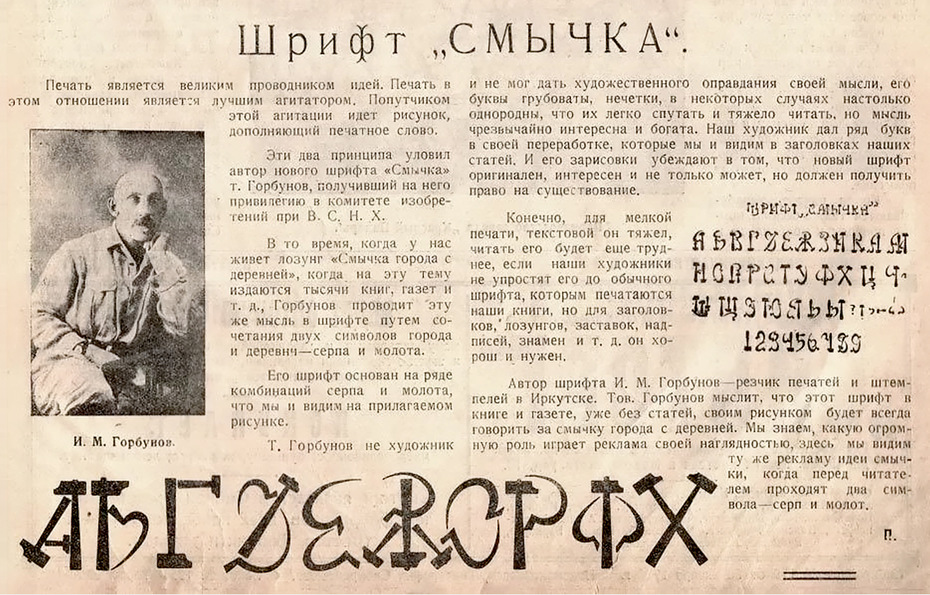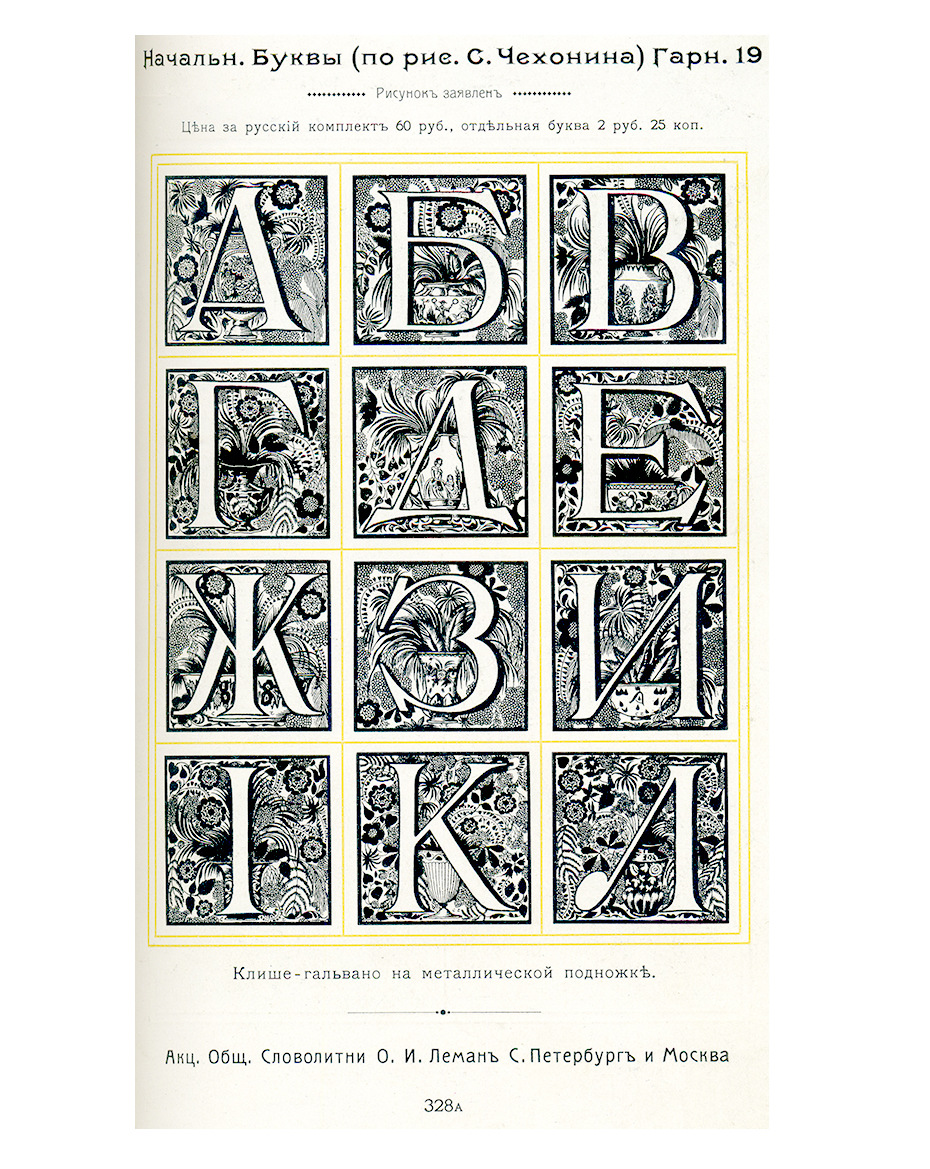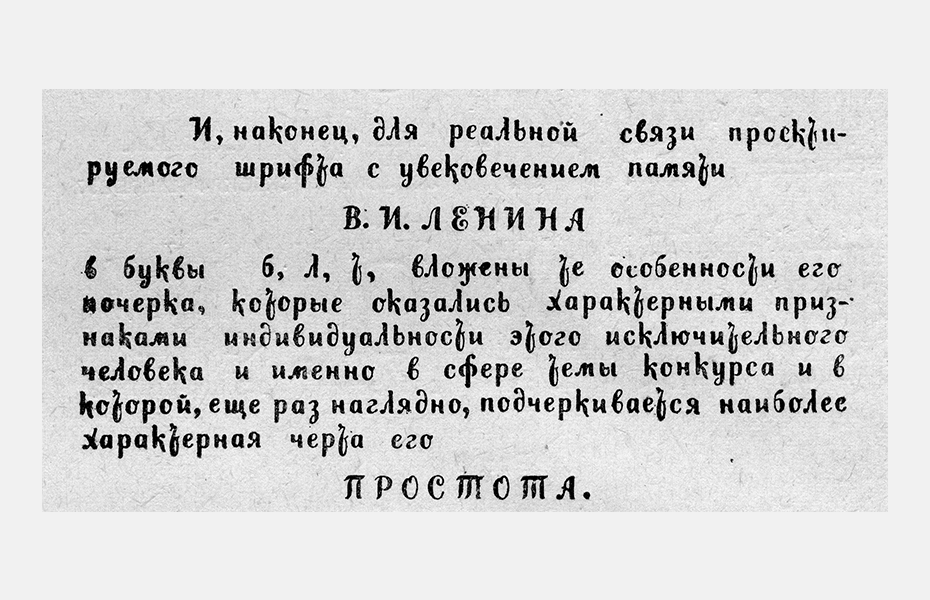
Из истории конкурсов шрифтового дизайна
Константин Головченко
еж­ду­на­род­ные кон­кур­сы шриф­то­во­го ди­зай­на се­го­дня — не­пло­хой мар­кер со­сто­я­ния ин­ду­стрии, при­чём не толь­ко про­фес­си­о­наль­ной, но и сту­ден­че­ской. Type design competition — ма­ши­на с от­ла­жен­ным за мно­го лет ме­ха­низ­мом и ин­ди­ви­ду­аль­ны­ми осо­бен­но­стя­ми в за­ви­си­мо­сти от ре­гла­мен­та, со­ста­ва жю­ри и ме­то­дов оцен­ки ра­бот. Всё ча­ще в кон­кур­сах по­яв­ля­ет­ся от­дель­ная ка­те­го­рия для не­ла­тин­ских шриф­тов, в том чис­ле и на осно­ве ки­рил­ли­цы. Ди­зай­нер, ис­то­рик шриф­та Кон­стан­тин Го­лов­чен­ко дол­гое вре­мя изу­чал ис­то­рию кон­кур­сов ки­рил­ли­че­ских шриф­тов и со­брал уни­каль­ные ар­хив­ные ма­те­ри­а­лы о шриф­тах-участ­ни­ках и ху­дож­ни­ках. Мы пуб­ли­ку­ем пер­вую часть его ис­сле­до­ва­ния — о том, ка­кие бы­ли кон­кур­сы в до­ре­во­лю­ци­он­ной Рос­сии и в пер­вые го­ды со­вет­ской вла­сти. Ре­дак­ция
Часть I. «Ка­кая ску­ка ри­со­вать шриф­ты».
Пер­вые кон­кур­сы шриф­то­во­го ди­зай­на
Са­мый дав­ний из из­вест­ных мне кон­кур­сов был ор­га­ни­зо­ван сло­во­лит­ней Ле­ма­на в 1912 го­ду. Пред­се­да­те­лем её прав­ле­ния на то вре­мя был Иосиф Иоси­фо­вич Ле­ман, один из сы­но­вей осно­ва­те­ля — Оси­па Ива­но­ви­ча Ле­ма­на. Иосиф Иоси­фо­вич уна­сле­до­вал не толь­ко свою до­лю в пред­при­я­тии от­ца, но и ис­крен­ний ин­те­рес к ти­по­гра­фи­ке, шриф­там и из­да­тель­ско­му де­лу. Кро­ме то­го, он был из­вест­ным биб­лио­фи­лом, кол­лек­ци­о­не­ром и ме­це­на­том, ав­то­ром двух книг — «Очерк раз­ви­тия и опи­са­ние ма­стер­ских Сло­во­лит­ни О. И. Ле­ман в Санкт-Пе­тер­бур­ге» и «Гра­вю­ра и ли­то­гра­фия».
Иосиф Ле­ман по­сто­ян­но ис­кал воз­мож­но­сти и по­ощрял лю­бые по­пыт­ки со­зда­ния но­вых ка­че­ствен­ных ри­сун­ков шриф­тов. На­при­мер, ко­гда в 1905 го­ду Игорь Эм­ма­ну­и­ло­вич Гра­барь со­би­рал­ся вы­пус­кать свой жур­нал «Вест­ник ис­кусств» (этот про­ект не уда­лось ре­а­ли­зо­вать), пред­по­ла­га­лось на­би­рать его но­вым шриф­том, ри­су­нок ко­то­ро­го дол­жен был ис­пол­нить М. В. До­бу­жин­ский. В пе­ре­пис­ке с ним Гра­барь со­об­щал:
«Се­го­дня же по­лу­чил и све­де­ния от­но­си­тель­но пер­спек­ти­вы иметь свой соб­ствен­ный шрифт. Если ри­су­нок Ле­ма­ну по­нра­вит­ся, то он ни­че­го не возь­мёт за от­лив­ку. <…> Ей-бо­гу, сто­ит ов­чин­ка вы­дел­ки. Шут­ка ли ска­зать: со­здать на­ко­нец-то ху­до­же­ствен­ный шрифт в Рос­сии. <…> Но на­до ид­ти на риск; если Ле­ма­ну, под­ле­цу, не по­нра­вит­ся, то Ва­ших 15 букв про­па­дут да­ром (проб­ных)».
Та­ким об­ра­зом, ор­га­ни­зо­ван­ный в 1912 го­ду кон­курс (по­след­ний срок сда­чи ра­бот — 15 ок­тя­бря) был оче­ред­ной по­пыт­кой со­зда­ния но­вых шриф­тов и по­пол­не­ния ас­сор­ти­мен­та сло­во­лит­ни, что да­ло бы ей пре­иму­ще­ство пе­ред до­воль­но силь­ны­ми кон­ку­рен­та­ми — в пер­вую оче­редь, сло­во­лит­ней Берт­голь­да.
Ге­ор­гий (Егор) Ива­но­вич Нар­бут [25 фе­вра­ля (9 мар­та) 1886, Нар­бу­тов­ка, Чер­ни­гов­ская гу­бер­ния — 23 мая 1920, Ки­ев]. Рус­ский и укра­ин­ский ху­дож­ник-гра­фик, ил­лю­стра­тор. Ма­стер ри­со­ван­но­го шриф­та, в пе­тер­бург­ский пе­ри­од жиз­ни Нар­бут офор­мил боль­шое ко­ли­че­ство книг в са­мых раз­ных жан­рах. На об­лож­ках и ти­туль­ных ли­стах он вир­ту­оз­но со­зда­вал об­раз­ные и пла­стич­ные над­пи­си  — от ими­та­ции древ­не­рус­ских по­чер­ков до ам­пир­ных букв. Фо­то не по­зд­нее 1917 го­да.
Ин­те­рес­ные сви­де­тель­ства об этом кон­кур­се мож­но по­черп­нуть из пе­ре­пис­ки од­но­го из участ­ни­ков, Г. И. Нар­бу­та, с же­ной. Ко вре­ме­ни опи­сы­ва­е­мых со­бы­тий Ге­ор­гий Ива­но­вич Нар­бут уже был при­знан­ным ху­дож­ни­ком-гра­фи­ком и со­сто­ял в ху­до­же­ствен­ном объ­еди­не­нии «Мир ис­кус­ства». Ещё в дет­стве шриф­ты вы­зы­ва­ли у не­го жи­вой ин­те­рес, в гим­на­зии он по соб­ствен­ной ини­ци­а­ти­ве пе­ре­ри­со­вы­вал бук­вы из Остро­ми­ро­ва Еван­ге­лия. По­том был пе­ре­езд в Пе­тер­бург, учё­ба у Би­ли­би­на, До­бу­жин­ско­го, Бак­ста, за­тем в Мюн­хе­не у Ш. Хол­ло­ши, мно­же­ство ис­пол­нен­ных для книг и жур­на­лов ил­лю­стра­ций, об­ло­жек, над­пи­сей.
Тем уди­ви­тель­нее в све­те вы­ше­из­ло­жен­но­го мо­гут вы­гля­деть ци­та­ты из не­ко­то­рых его пи­сем:
«Ма­ло я сей­час те­бе пи­шу; ты не оби­жай­ся, моя ра­дость. Ведь я пи­шу толь­ко ве­че­ром и по­чти все­гда уста­лый к это­му вре­ме­ни. Ра­бо­таю сей­час над шриф­том: ад­ская ску­ка… Если бы ты зна­ла, Ве­ру­ся, ка­кая ску­ка ри­со­вать шриф­ты, то есть бук­вы. Но еще при­дет­ся си­деть за этим дня два-три, а я уже по­чти не имею сил… Се­го­дня си­дел один, как перст, це­лый день и со­всем не от­ры­вал­ся от ра­бо­ты. Устал, как ты мо­жешь пред­ста­вить, не­ве­ро­ят­но, очень. Глав­ное, что эта ра­бо­та та­кая не­за­хва­ты­ва­ю­щая, скуч­ная-пре­скуч­ная».
За­кон­чив ра­бо­ту и от­пра­вив к сро­ку об­раз­цы, Нар­бут яв­но ощу­ща­ет об­лег­че­ние: «Сей­час не­мно­го опра­вил­ся по­сле пи­са­ния раз­лич­ных шриф­тов… Я се­бя чув­ствую от­лич­но, бодро и хо­ро­шо, а глав­ное, про­шло то гне­ту­щее на­стро­е­ние и апа­тия, пре­сле­до­вав­шие ме­ня всё вре­мя на про­шлой не­де­ле».
Воз­ни­ка­ет есте­ствен­ный во­прос: как же мог на­пи­сать по­доб­ное этот ма­стер, про­жив­ший до­воль­но ко­рот­кую, но на­сы­щен­ную жизнь и оста­вив­ший це­лый ряд уче­ни­ков и по­сле­до­ва­те­лей, ма­стер, в на­сле­дии ко­то­ро­го — мно­же­ство ра­бот, и се­го­дня слу­жа­щих вдох­но­ве­ни­ем для ди­зай­не­ров шриф­та?
Воз­мож­но, под­сказ­кой для от­ве­та мо­жет слу­жить ра­бо­та, за­няв­шая на этом кон­кур­се пер­вое ме­сто. Она при­над­ле­жит дру­го­му чле­ну «Ми­ра ис­кус­ства», Сер­гею Че­хо­ни­ну. Его про­ект дей­стви­тель­но был ре­а­ли­зо­ван в ме­тал­ле в ка­че­стве на­бор­но­го шриф­та. Од­на­ко шрифт этот до­воль­но спе­ци­фи­че­ский — он был пред­на­зна­чен для бук­виц. От­ли­чие по­доб­ных шриф­тов в том, что бук­вы в них, как пра­ви­ло, не пред­по­ла­га­ют вза­и­мо­дей­ствия друг с дру­гом, яв­ля­ясь по су­ти от­дель­ным эле­мен­том на­бо­ра.
По­бе­да имен­но та­кой ра­бо­ты мо­жет го­во­рить о том, что для Нар­бу­та и осталь­ных ху­дож­ни­ков, при­вык­ших ри­со­вать над­пи­си, за­да­ча по со­зда­нию на­бор­но­го шриф­та ока­за­лась слиш­ком тя­жёлой. Ведь в на­ри­со­ван­ной над­пи­си каж­дая бук­ва вза­и­мо­дей­ству­ет лишь со сво­и­ми со­се­дя­ми по стро­ке, на­бор­ный же шрифт тре­бу­ет мак­си­маль­но гар­мо­нич­но­го со­че­та­ния всех зна­ков в лю­бых ком­би­на­ци­ях. По­хо­жие си­ту­а­ции мож­но до­ста­точ­но ча­сто на­блю­дать и сей­час, ко­гда ди­зай­нер пы­та­ет­ся со­здать шрифт на осно­ве ри­со­ван­ных букв то­го или ино­го ху­дож­ни­ка, но по­сле точ­ной их от­ри­сов­ки в век­тор­ном фор­ма­те осо­зна­ёт, что в та­ком ви­де они го­дят­ся лишь для вос­про­из­ве­де­ния ис­ход­ной над­пи­си. По вос­по­ми­на­ни­ям со­вре­мен­ни­ков, Нар­бут до кон­ца жиз­ни на­де­ял­ся со­здать на­бор­ный шрифт, «но со­зда­вать шрифт — это „боль­шая мо­ро­ка“: нуж­но про­ра­ба­ты­вать каж­дую бук­ву, каж­дую ме­лочь при­ни­мать во вни­ма­ние, вы­ме­рять».
На­бор­ная бук­ви­ца С. Че­хо­ни­на. Жур­нал «Рус­ское ис­кус­ство» №1. 1923.
Тем не ме­нее приём, с по­мо­щью ко­то­ро­го по­бе­дил Че­хо­нин, на мой взгляд, впол­не при­ме­ним и в на­ше вре­мя. И се­го­дня ди­зай­нер, спо­соб­ный со­зда­вать по-на­сто­я­ще­му ин­те­рес­ные шриф­то­вые фор­мы, но не име­ю­щий до­ста­точ­но на­вы­ков, вре­ме­ни, тер­пе­ния или же­ла­ния для то­го, что­бы вы­пол­нять кро­пот­ли­вую ра­бо­ту по со­зда­нию «обыч­но­го» шриф­та, мо­жет по­про­бо­вать се­бя в раз­ра­бот­ке де­ко­ра­тив­ных ини­ци­а­лов — и та­кой про­ект име­ет шанс быть от­ме­чен­ным на кон­кур­се.
За­вер­шая рас­сказ об ор­га­ни­зо­ван­ном сло­во­лит­ней Ле­ма­на кон­кур­се, нуж­но упо­мя­нуть, что он пред­по­ла­гал де­неж­ное воз­на­гра­жде­ние. Точ­ный его раз­мер нам, к со­жа­ле­нию, не­из­ве­стен, но Нар­бут, на­при­мер, в слу­чае по­бе­ды на вы­ру­чен­ные день­ги рас­счи­ты­вал ку­пить ро­яль.
Со­вет­ские кон­кур­сы 1920-х го­дов
Сле­ду­ю­щие кон­кур­сы, ко­то­рые мы рас­смот­рим, от­но­сят­ся к 20-м го­дам про­шло­го ве­ка. В 1927 го­ду бу­ду­щий член-кор­ре­спон­дент Ака­де­мии на­ук, про­фес­сор Алек­сей Алек­се­е­вич Си­до­ров, не­до­уме­вая, пи­сал: «По­пыт­ки ре­фор­мы очер­та­ния шриф­та, со­зда­ния но­во­го не шли даль­ше ор­га­ни­за­ции не­сколь­ких кон­кур­сов, кон­чив­ших­ся бес­плод­но. По­че­му? В ма­сте­рах у нас не­до­стат­ка нет. Нет не­до­стат­ка и в уме­нии клас­си­фи­ци­ро­вать и ра­зо­брать­ся».
Дей­стви­тель­но, в то вре­мя пред­при­ни­мал­ся ряд ини­ци­а­тив по про­ве­де­нию кон­кур­сов, ни один из ко­то­рых, как спра­вед­ли­во от­ме­чал А. А. Си­до­ров, не дал прак­ти­че­ских ре­зуль­та­тов.
Пер­вый со­вет­ский шриф­то­вой кон­курс от­но­сит­ся, ве­ро­ят­но, к 1920 го­ду. Он был ор­га­ни­зо­ван Пет­ро­град­ским от­де­ле­ни­ем Го­су­дар­ствен­но­го кни­го­из­да­тель­ства, рас­про­стра­нив­шим сле­ду­ю­щее объ­яв­ле­ние:
«На­сто­я­щим до­во­дит[ся] до све­де­ния всех ху­дож­ни­ков-гра­вё­ров, гра­вё­ров-пу­ан­со­ни­стов и гра­вё­ров-ли­то­гра­фов, что… ор­га­ни­зо­ван кон­курс по со­зда­нию но­вых рус­ских шриф­тов, а имен­но:
1) шриф­та для учеб­ни­ков и учеб­ных по­со­бий,
2) шриф­та для книг бел­ле­три­сти­че­ско­го со­дер­жа­ния, жур­на­лов и га­зет и
3) шриф­та для книг и жур­на­лов, рос­кош­но из­да­ва­е­мых»
Так­же нуж­но от­ме­тить кон­курс, ор­га­ни­зо­ван­ный в 1923 го­ду. В де­ка­бре 1922 го­да по ини­ци­а­ти­ве К. С. Кузь­мин­ско­го при Го­су­дар­ствен­ном из­да­тель­стве бы­ла со­зда­на «Ко­мис­сия по изу­че­нию рус­ских ил­лю­стри­ро­ван­ных из­да­ний», поз­же пе­ре­име­но­ван­ная в «Ко­мис­сию по изу­че­нию ис­кус­ства кни­ги». Её пред­се­да­те­лем стал сам Кузь­мин­ский, в со­став во­шли В. Я. Ада­рю­ков, К. С. Ва­х­ра­ме­ев, М. А. До­бров, А. Г. Ка­лаш­ни­ков, Н. П. Ки­се­лёв, И. И. Ла­за­рев­ский, В. П. По­лон­ский, А. А. Си­до­ров, В. А. Фа­вор­ский, В. Д. Фа­ли­ле­ев, П. П. Ши­ба­нов, М. И. Щел­ку­нов, П. Д. Эт­тин­гер и се­кре­тарь — В. В. Голь­цев.
В са­мом на­ча­ле её ра­бо­ты был под­нят во­прос о со­зда­нии но­во­го ти­по­граф­ско­го шриф­та, так как су­ще­ству­ю­щие при­зна­ва­лись уста­рев­ши­ми и не от­ве­ча­ю­щи­ми тре­бо­ва­ни­ям со­вре­мен­но­сти. На за­се­да­ни­ях этой ко­мис­сии бы­ло за­слу­ша­но мно­же­ство до­кла­дов о шриф­те: «Вве­де­ние в те­о­рию шриф­тов» А. А. Си­до­ро­ва, «Прин­ци­пы кра­со­ты шриф­та» М. И. Щел­ку­но­ва, «Биб­лио­гра­фи­че­ский ука­за­тель „Рус­ские ти­по­граф­ские шриф­ты“» В. Я. Ада­рю­ко­ва, «Что тре­бу­ет от шриф­тов про­цесс чте­ния» В. И. Яз­виц­ко­го, «Ком­по­зи­ци­он­ные осно­вы шриф­та» В. Д. Фа­ли­ле­е­ва, «Шрифт для дет­ской и на­род­ной ли­те­ра­ту­ры» К. С. Ва­х­ра­ме­е­ва, «Ме­то­ди­ка ис­сле­до­ва­ния фи­зио­ло­ги­че­ско­го дей­ствия книж­но­го шриф­та» А. Г. Ка­лаш­ни­ко­ва, «Шриф­ты для ти­туль­ных ли­стов» Н. В. Маш­ков­це­ва, «О книж­ных укра­ше­ни­ях» М. А. До­бро­ва и др.
За­тем был ор­га­ни­зо­ван за­кры­тый кон­курс на со­зда­ние экс­либ­ри­сов для Биб­лио­те­ки Го­сиз­да­та и Ар­хи­ва Рос­сий­ской Цент­раль­ной книж­ной па­ла­ты, по­сле успеш­но­го за­вер­ше­ния ко­то­ро­го на за­се­да­нии 3 ок­тя­бря 1923 го­да бы­ло при­ня­то ре­ше­ние о про­ве­де­нии за­кры­то­го кон­кур­са на со­зда­ние книж­но­го шриф­та для на­бо­ра дет­ской ли­те­ра­ту­ры. К уча­стию в нём при­вле­ка­лись В. А. Фа­вор­ский, Н. И. Пис­ка­рёв, Н Н. Ку­пре­я­нов, В. Д. Фа­ли­ле­ев, А. Н. Лео и дру­гие ху­дож­ни­ки Моск­вы и Ле­нин­гра­да. За осно­ву пред­ла­га­лось взять Ла­тин­ский шрифт. В кон­це сен­тя­бря про­шло об­су­жде­ние пред­став­лен­ных ра­бот, из ко­то­рых ни од­на не бы­ла при­зна­на в долж­ной ме­ре удо­вле­тво­ря­ю­щей усло­ви­ям.
Са­мым же из­вест­ным из ран­них со­вет­ских шриф­то­вых кон­кур­сов яв­ля­ет­ся кон­курс на со­зда­ние так на­зы­ва­е­мо­го Ле­нин­ско­го шриф­та. По­сле смер­ти Вла­ди­ми­ра Ильи­ча Ле­ни­на 21 ян­ва­ря 1924 го­да по всей стра­не на­ча­ли про­во­дить­ся раз­лич­ные ме­ро­при­я­тия по уве­ко­ве­чи­ва­нию па­мя­ти во­ждя. Пред­се­да­тель го­су­дар­ствен­но­го тре­ста ВСНХ «По­ли­граф» М. О. Шен­де­ро­вич на за­се­да­нии прав­ле­ния пред­ло­жил объ­явить кон­курс «на из­го­тов­ле­ние ри­сун­ка но­во­го шриф­та, при­сво­ив ему на­име­но­ва­ние „Ле­нин­ско­го“, и к не­му со­от­вет­ству­ю­ще­го ри­сун­ка ор­на­мен­та, за­ста­вок, кон­цо­вок и ини­ци­а­лов». Пред­ло­же­ние бы­ло одо­бре­но, и вско­ре объ­яв­ле­ния о кон­кур­се по­яви­лись в цен­траль­ных га­зе­тах, кро­ме то­го, пе­ча­та­лись спе­ци­аль­ные про­спек­ты с по­дроб­ны­ми усло­ви­я­ми, вы­сы­лав­ши­е­ся по тре­бо­ва­нию.
Объ­яв­ле­ние о про­ве­де­нии кон­кур­са на со­зда­ние Ле­нин­ско­го шриф­та в га­зе­те «Из­ве­стия» №42. 1924.
Но­вый шрифт пред­на­зна­чал­ся для на­бо­ра круп­но­ти­раж­ных по­пу­ляр­ных книг и бро­шюр для не­ква­ли­фи­ци­ро­ван­но­го чи­та­те­ля. С учё­том это­го основ­ным тре­бо­ва­ни­ем к не­му бы­ла удо­бо­чи­та­е­мость, «что­бы при чте­нии не утом­ля­лось зре­ние чи­та­те­ля; ри­су­нок букв про­стой, без вы­чур­но­стей». Ра­ди её улуч­ше­ния до­пус­ка­лись и из­ме­не­ния в при­выч­ных ри­сун­ках букв:
«Так как су­ще­ству­ю­щий ал­фа­вит име­ет огра­ни­чен­ное чис­ло букв со штри­ха­ми, вы­хо­дя­щи­ми за ниж­нюю и верх­нюю ли­нию стро­ки, что при­даёт строч­кам кни­ги од­но­об­ра­зие и за­труд­ня­ет чте­ние, ху­дож­ни­кам пре­до­став­ля­ет­ся пра­во, пу­тём ча­стич­но­го из­ме­не­ния букв, уве­ли­чить чис­ло букв с вы­хо­дя­щи­ми вниз и вверх штри­ха­ми».
Ор­на­мен­том пред­по­ла­га­лось ил­лю­стри­ро­вать идею мо­гу­ще­ства тру­да. Он дол­жен был со­сто­ять из не­боль­шо­го чис­ла не­слож­ных эле­мен­тов, до­пус­кав­ших ком­би­ни­ро­ва­ние в раз­лич­ных со­че­та­ни­ях.
Все ра­бо­ты сле­до­ва­ло ис­пол­нять чёр­ной ту­шью на плот­ной бе­лой бу­ма­ге, они долж­ны бы­ли вклю­чать пол­ный на­бор про­пис­ных и строч­ных букв рус­ско­го ал­фа­ви­та, циф­ры, зна­ки пре­пи­на­ния, ини­ци­а­лы, а так­же по 5 ри­сун­ков за­ста­вок и кон­цо­вок и не­огра­ни­чен­ное чис­ло ор­на­мен­тов (по же­ла­нию ав­то­ра). Вы­со­та строч­ных на пре­до­став­ля­е­мом ри­сун­ке долж­на бы­ла со­став­лять 1 см, при этом их вы­со­та при пе­ча­ти долж­на бы­ла быть не ме­нее 1,75 мм, а тол­щи­на основ­ных штри­хов — не ме­нее 0,25 мм. Ор­на­мент, за­став­ки, кон­цов­ки и ини­ци­а­лы до­пус­ка­лось пред­став­лять уве­ли­чен­ны­ми до 8 раз от­но­си­тель­но раз­ме­ра при пе­ча­ти.
В укра­ин­ской прес­се, од­но­вре­мен­но с одо­бри­тель­ны­ми сло­ва­ми о кон­кур­се, по­яви­лись за­ме­ча­ния о том, что «трест „По­ли­граф“, ко­то­рый, кста­ти, на­зы­ва­ет­ся со­юз­ным тре­стом, за­был о том, что рус­ским ал­фа­ви­том поль­зу­ют­ся для пе­ча­ти не толь­ко рус­ских, но и укра­ин­ских и бе­ло­рус­ских книг и что сле­до­ва­ло бы рус­ский ал­фа­вит с учётом это­го до­пол­нить укра­ин­ски­ми (є, ї, ґ) и бе­ло­рус­ски­ми (ё, ў) бук­ва­ми. Если же это­го до­пол­не­ния не про­изой­дёт, то и укра­ин­ская, и бе­ло­рус­ская кни­га, на­бран­ная Ле­нин­ским шриф­том, бу­дет ис­пор­че­на встав­ка­ми вы­ше­упо­мя­ну­тых букв из дру­го­го — го­во­ря язы­ком пе­чат­ни­ка, „чу­жо­го“ шриф­та». Име­лось в ви­ду, ра­зу­ме­ет­ся, не до­пол­не­ние рус­ско­го ал­фа­ви­та но­вы­ми бук­ва­ми, а рас­ши­ре­ние зна­ко­во­го со­ста­ва кон­курс­ных про­ек­тов.
Объ­яв­ле­ние о про­ве­де­нии кон­кур­са на со­зда­ние Ле­нин­ско­го шриф­та в га­зе­те «Вест­ник Ле­нин­град­ско­го со­ве­та» №20. 1924.
В со­став жю­ри во­шли ини­ци­а­тор кон­кур­са М. О. Шен­де­ро­вич и член прав­ле­ния тре­ста «По­ли­граф» В. В. Ни­ко­ла­ев, пред­се­да­тель Со­ю­за пе­чат­ни­ков Н. И. Дер­бы­шев, пред­ста­ви­тель Го­сиз­да­та С. И. Ре­ше­тов, пред­ста­ви­тель ВХУ­ТЕ­МА­Са про­фес­сор Н. Я. Пав­ли­нов и оку­лист — про­фес­сор К. В. Сне­ги­рёв. Кро­ме то­го, чле­ном жю­ри был гра­вёр-пу­ан­со­нист И. И. Ле­бе­дев — опыт­ней­ший спе­ци­а­лист сло­во­лит­ни им. III Ин­тер­на­ци­о­на­ла (быв­шей Ле­ма­на) с 40-лет­ним на тот мо­мент ста­жем. В 1918 го­ду имен­но ему по­ру­чи­ли из­го­тов­ле­ние пер­вой со­вет­ской го­су­дар­ствен­ной пе­ча­ти.
Сро­ки про­ве­де­ния бы­ли до­воль­но сжа­ты­ми: пер­вые объ­яв­ле­ния в прес­се по­яви­лись в на­ча­ле фе­вра­ля, в то вре­мя как по­след­ний срок для сда­чи ра­бот в Моск­ве на­зна­чал­ся сна­ча­ла на 1 мая, а за­тем был пе­ре­не­сён на 12 ча­сов дня 5 мая, ра­бо­ты же из про­вин­ции долж­ны бы­ли быть от­прав­ле­ны по по­чте не поз­же 30 ап­ре­ля. Та­ким об­ра­зом, на раз­ра­бот­ку но­во­го шриф­та от­во­ди­лось три ме­ся­ца. Ре­зуль­та­ты кон­кур­са над­ле­жа­ло опуб­ли­ко­вать в га­зе­те «Из­ве­стия» не по­зд­нее 1 июня 1924 го­да. По­бе­див­ший шрифт пред­по­ла­га­лось от­пус­кать по ми­ни­маль­ной це­не. Каж­дый про­ект снаб­жал­ся де­ви­зом, так же как и за­пе­ча­тан­ный кон­верт, со­дер­жа­щий ин­фор­ма­цию о  его ав­то­ре.
Для по­бе­ди­те­лей бы­ли уста­нов­ле­ны три де­неж­ные пре­мии: пер­вая — 2500; вто­рая — 1500 и тре­тья — 1000 чер­вон­ных ру­блей. Чер­вон­цы бы­ли вве­де­ны в об­ра­ще­ние в 1922 го­ду, за два го­да до объ­яв­ле­ния кон­кур­са, и, бла­го­да­ря зо­ло­то­му обес­пе­че­нию, счи­та­лись до­ста­точ­но на­дёж­ным де­неж­ным сред­ством. Пре­ми­ро­ван­ные ра­бо­ты пе­ре­хо­ди­ли в соб­ствен­ность тре­ста «По­ли­граф».
Пер­вое за­се­да­ние жю­ри со­сто­я­лось 15 мая. К это­му вре­ме­ни бы­ло при­сла­но 33 ра­бо­ты, три из ко­то­рых бы­ли от­кло­не­ны по фор­маль­ным осно­ва­ни­ям. 17 про­ек­тов по­сту­пи­ло из Моск­вы, 6 — из Ле­нин­гра­да, по 2 — из Ки­е­ва, Харь­ко­ва и Во­ло­гды и по од­но­му — из Тве­ри, Ир­кут­ска, Алек­сан­дров­ска и с Зе­ле­но­доль­ско­го ма­ши­но­стро­и­тель­но­го за­во­да «Крас­ный ме­тал­лист» в Та­тар­ской АССР. Ещё од­на от­кло­нён­ная ра­бо­та по­сту­пи­ла, ве­ро­ят­но, зна­чи­тель­но поз­же сро­ка, и от­ку­да она бы­ла от­прав­ле­на, уста­но­вить не уда­лось.
При рас­смот­ре­нии про­ек­тов учи­ты­ва­лось со­от­вет­ствие усло­ви­ям кон­кур­са, ху­до­же­ствен­ность и са­мо­быт­ность (то есть не­по­хо­жесть на су­ще­ству­ю­щие шриф­ты). В ито­ге жю­ри при­ня­ло ре­ше­ние не при­су­ждать пре­мий, так как ни один из про­ек­тов не удо­вле­тво­рял тре­бо­ва­ни­ям кон­кур­са. Тем не ме­нее бы­ло от­ме­че­но 4 ра­бо­ты, при­слан­ных под де­ви­за­ми «Один я — ни­что, с ва­ми — всё», «Крас­ный квад­рат», «Серп и Ко­лос» и «Тре­тий фронт», за­став­ки, кон­цов­ки и ви­ньет­ки ко­то­рых мог­ли быть ча­стич­но ис­поль­зо­ва­ны. Трест «По­ли­граф» при­гла­сил их ав­то­ров в ме­сяч­ный срок явить­ся для пе­ре­го­во­ров.
Кто же бы­ли ав­то­ры при­слан­ных ра­бот и что имен­но они пред­ла­га­ли? Нуж­но от­ме­тить, что ин­фор­ма­цию об этом кон­кур­се при­шлось со­би­рать бук­валь­но по кру­пи­цам, по­сколь­ку при­слан­ные ра­бо­ты, если толь­ко ав­то­ры не яви­лись за ни­ми лич­но или не при­сла­ли «со­от­вет­ству­ю­щее ко­ли­че­ство по­что­вых ма­рок» для пе­ре­сыл­ки, уни­что­жа­лись.
Итак, пер­вым нуж­но на­звать Алек­сан­дра Пав­ло­ви­ча Вла­ды­чу­ка. Не­смот­ря на то что фак­ти­че­ски в кон­кур­се по­бе­ди­те­лей не бы­ло, в сво­ей ста­тье в жур­на­ле «Гра­фи­че­ское ис­кус­ство» (поз­же пе­ре­име­но­ван­ном в «По­ли­гра­фи­че­ское про­из­вод­ство», а за­тем в «По­ли­гра­фию») он пи­сал:
«На мою до­лю вы­па­ла честь быть ав­то­ром ра­бо­ты, при­знан­ной кон­курс­ной ко­мис­си­ей луч­шей как по ори­ги­наль­но­сти, так и по пра­виль­но­сти под­хо­да к раз­ре­ше­нию на­сто­я­щей за­да­чи, но сте­пень от­ступ­ле­ния от су­ще­ству­ю­ще­го шриф­та ока­за­лась на­столь­ко зна­чи­тель­ной, что про­ве­сти в жизнь этот шрифт ко­мис­сия не ре­ши­лась. Во­прос остал­ся от­кры­тым».
Бла­го­да­ря этой пуб­ли­ка­ции се­го­дня под Ле­нин­ским шриф­том обыч­но под­ра­зу­ме­ва­ют имен­но эту ра­бо­ту.
А. П. Вла­ды­чук (1893, Моск­ва — 10 ап­ре­ля 1958) — че­ло­век очень ин­те­рес­ной судь­бы. Он окон­чил Стро­га­нов­ское учи­ли­ще в Моск­ве, за­тем был при­зван в ар­мию и от­прав­лен в Тур­ке­стан. По­сле уста­нов­ле­ния Со­вет­ской вла­сти в Турк­ме­нии он ри­су­ет книж­ные об­лож­ки и ка­ри­ка­ту­ры, оформ­ля­ет агит­по­ез­да, вме­сте со сво­им од­но­пол­ча­ни­ном Р. М. Ма­зе­лем со­зда­ет «Удар­ную шко­лу ис­кусств Вос­то­ка» (УШИВ), сни­ма­ет муль­ти­пли­ка­ци­он­ные, до­ку­мен­таль­ные и ху­до­же­ствен­ные филь­мы на сту­дии «Турк­мен­фильм», а так­же участ­ву­ет в со­зда­нии гер­ба Турк­мен­ской ССР. Кро­ме то­го, Алек­сандр Пав­ло­вич был спорт­сме­ном и изоб­ре­та­те­лем. По соб­ствен­но­му про­ек­ту он по­стро­ил не­сколь­ко ру­ле­пе­дов — ве­ло­си­пе­дов с при­во­дом на оба ко­ле­са — и в 1935 го­ду ор­га­ни­зо­вал на них ве­ло­про­бег по марш­ру­ту Аш­ха­бад — Тби­ли­си — Моск­ва.
Ве­ло­про­бег по марш­ру­ту Аш­ха­бад — Тби­ли­си — Моск­ва на ру­ле­пе­дах.
И вот ко всем этим свер­ше­ни­ям до­бав­ля­ет­ся уча­стие в шриф­то­вом кон­кур­се. На са­мом де­ле пред­ло­жен­ное Вла­ды­чу­ком бы­ло бóль­шим, чем про­сто но­вый ти­по­граф­ский шрифт. По су­ти, это был про­ект ре­фор­мы, ко­то­рую он сам ста­вил в один ряд с пет­ров­ской:
«Рос­сия за свою ис­то­рию уже од­на­жды пе­ре­ме­ни­ла шрифт, стро­го сле­дуя за­ко­ну со­от­вет­ствия фор­мы с мыс­лью. Пер­вый сла­вян­ский шрифт пред­став­лял со­бою как бы ха­рак­тер­ное гра­фи­че­ское изоб­ра­же­ние тя­жё­лой цер­ков­но-бо­яр­ской Ру­си. Вто­рой не мог быть ни­ка­ким дру­гим, кро­ме шриф­та, ко­то­рым поль­зо­вал­ся За­пад, так как Пётр I пре­об­ра­зо­вал ази­ат­скую Русь в ев­ро­пей­скую им­пе­рию. Как ла­тин­ский, так и рус­ский-пет­ров­ский шриф­ты, сво­и­ми внеш­ни­ми фор­ма­ми да­ют ха­рак­тер­ное изоб­ра­же­ние ка­пи­та­ли­сти­че­ских го­су­дарств За­па­да. Ими этот шрифт был со­здан и оформ­лен для вы­ра­же­ния сво­их соб­ствен­ных бур­жу­аз­ных осо­бен­но­стей.
Рос­сия те­перь пе­ре­жи­ва­ет тре­тью, са­мую зна­чи­тель­ную эпо­ху. На этот раз пре­об­ра­зо­ва­те­лем яв­ля­ет­ся уже не царь, не от­дель­ный ге­рой, а це­лая пар­тия, со­здан­ная во­ждём ра­бо­чих и кре­стьян все­го ми­ра В. И. Ле­ни­ным. От ми­ро­вой, ка­пи­та­ли­сти­че­ской гид­ры от­ко­лол­ся ку­сок и за­све­тил­ся яр­ким со­ци­а­ли­сти­че­ским све­том. На ме­сте бур­жу­аз­ной, им­пе­ри­а­ли­сти­че­ской, с ре­ли­ги­оз­ны­ми пред­рас­суд­ка­ми Рос­сии воз­ник­ло пер­вое в ми­ре со­ци­а­ли­сти­че­ское го­су­дар­ство, ха­рак­тер­ное сво­ей про­сто­той, си­лой и све­же­стью. Яс­но, что ни пет­ров­ский, ни ла­тин­ский шриф­ты та­кое го­су­дар­ство не удо­вле­тво­рят. Нуж­но со­здать свой соб­ствен­ный шрифт, ко­то­рый яв­лял­ся бы ха­рак­тер­ным гра­фи­че­ским изоб­ра­же­ни­ем со­ци­а­ли­сти­че­ско­го го­су­дар­ства — про­сто­го, силь­но­го и све­же­го».
Ав­тор пред­ла­гал объ­еди­нить фор­мы про­пис­ных и строч­ных букв, а так­же их ру­ко­пис­ные фор­мы, что­бы об­лег­чить обу­че­ние гра­мо­те: «Ча­сто стал­ки­ва­ешь­ся с при­ме­ром, ко­гда уче­ник, осо­бен­но взрос­лый, хо­ро­шо усво­ив­ший пе­чат­ную бук­ву, ни­как не мо­жет оси­лить ту же пись­мен­ную. Ему при­хо­дит­ся изу­чать две, а то и все че­ты­ре аз­бу­ки».
Про­ект А. П. Вла­ды­чу­ка для кон­кур­са на со­зда­ние Ле­нин­ско­го шриф­та.
В ста­ра­нии ис­поль­зо­вать мак­си­маль­но при­выч­ные для про­сто­го на­ро­да фор­мы эле­мен­ты по­стро­е­ния букв при­ме­ня­лись са­мые про­стые: «пал­ка и за­ко­рюч­ка». Все они име­ли оди­на­ко­вую тол­щи­ну. Са­ми бук­вы бы­ли со­зна­тель­но сде­ла­ны ши­ро­ки­ми, так как «ши­ро­кий шрифт, без­услов­но, лег­че чи­та­ет­ся и мень­ше утом­ля­ет зре­ние, осо­бен­но ма­ло при­выч­но­го че­ло­ве­ка. По­смот­ри­те на по­черк кре­стья­ни­на или ра­бо­че­го или да­же каж­до­го из нас. Мы все пи­шем бук­ва­ми, ко­то­рые по сво­ей фор­ме укла­ды­ва­ют­ся в квад­рат (ко­неч­но, есть ис­клю­че­ния). По­это­му и со­от­вет­ству­ю­щая фор­ма в пе­ча­ти для масс бу­дет чем-то зна­ко­мым, близ­ким, сво­им». Впро­чем, для раз­лич­ных спра­воч­ных из­да­ний пред­по­ла­га­лось ис­поль­зо­вать та­кой же шрифт, но бо­лее уз­кий. Глас­ным бук­вам бы­ла при­да­на оваль­ная фор­ма, а со­глас­ным — пря­мо­ли­ней­ная для со­от­вет­ствия «вы­ра­же­нию зву­ко­вой ас­со­ци­а­ции в фор­ме».
Пред­по­ла­га­лись из­ме­не­ния и в ис­поль­зо­ва­нии зна­ка пе­ре­но­са. Его нуж­но бы­ло ста­вить «не в кон­це стро­ки, вме­сто по­след­ней бук­вы, а под по­след­ней бук­вой; этим са­мым уни­что­жит­ся не­ак­ку­рат­ность в пе­ча­ти, так как зна­ки пе­ре­но­са да­ют впе­чат­ле­ние не­до­бран­ной стро­ки и пра­вый край стра­ни­цы вы­гля­дит рва­ным».
«Вла­ди­мир Ильич Ле­нин с его зна­ме­ни­той яс­ной го­ло­вой ед­ва ли бы одо­брил это изоб­ре­те­ние, ведь его идея все­об­ще­го обу­че­ния со­всем не сво­ди­лась к то­му, что­бы за­гро­мо­ждать го­ло­вы по­доб­ным хит­ро­ум­ным рус­ско-ар­мян­ским шриф­том»
Кро­ме то­го, ав­тор «при­дер­жи­вал­ся не толь­ко на­род­но­го пись­ма, но и по­чер­ка Вла­ди­ми­ра Ильи­ча (бук­вы: К, Л, Я, Б, Д, Е, Э, З, Р)». В. Н. Ле­вит­ский на это воз­ра­жал, что «Вла­ди­мир Ильич Ле­нин с его зна­ме­ни­той яс­ной го­ло­вой ед­ва ли бы одо­брил по­доб­ное изоб­ре­те­ние, ведь его идея все­об­ще­го обу­че­ния со­всем не сво­ди­лась к то­му, что­бы за­гро­мо­ждать го­ло­вы по­доб­ным хит­ро­ум­ным рус­ско-ар­мян­ским шриф­том».
Ин­те­рес­но, что фор­мы, схо­жие с те­ми, ко­то­рые А. П. Вла­ды­чук в 20-е го­ды пред­ла­гал для удо­бо­чи­та­е­мо­сти, на­хо­дят при­ме­не­ние и се­го­дня — на­при­мер, в шриф­те Оле­га Ма­цу­е­ва Siberian, от­ме­чен­ном на кон­кур­се «Со­вре­мен­ная ки­рил­ли­ца 2014». Толь­ко в нём они до­бав­ле­ны как сти­ли­сти­че­ские ва­ри­ан­ты, что­бы поль­зо­ва­тель, по сло­вам ав­то­ра, сам мог вы­би­рать, «на­сколь­ко „от­мо­ро­жен­ной“ бу­дет его ти­по­гра­фи­ка».
Сле­ду­ю­щий про­ект, пред­став­лен­ный под де­ви­зом «Тре­тий фронт», при­над­ле­жал Вла­ди­ми­ру Ни­ко­ла­е­ви­чу Ад­ри­а­но­ву. Его имя так­же до­ста­точ­но хо­ро­шо из­вест­но — и как изоб­ре­та­те­ля вой­ско­во­го ком­па­са с фос­фо­рес­ци­ру­ю­щей под­свет­кой, но­ся­ще­го его имя, и как вы­да­ю­ще­го­ся кар­то­гра­фа, ав­то­ра ря­да шриф­тов для при­ме­не­ния в кар­то­гра­фии, и как со­зда­те­ля пер­во­го гер­ба СССР и гер­ба Та­джик­ской ССР. Кро­ме то­го, он яв­ля­ет­ся ав­то­ром од­но­го из пер­вых со­вет­ских на­бор­ных шриф­тов, со­здан­но­го по за­ка­зу «Го­зна­ка», ко­то­рый ис­поль­зу­ет­ся по сей день.
В при­слан­ной на кон­курс ра­бо­те Ад­ри­а­нов пред­ло­жил «мак­си­маль­но сбли­зить фор­мы пе­чат­ных букв с ру­ко­пис­ны­ми для об­лег­че­ния усво­е­ния гра­мо­ты и по­сле­ду­ю­ще­го чте­ния книж­ных тек­стов. Од­но­вре­мен­но бы­ла сде­ла­на по­пыт­ка гра­фи­че­ски со­гла­со­вать рус­ские бук­вы с ла­тин­ски­ми. В част­но­сти, он пред­ла­гал вер­нуть зву­ку „и“ ла­тин­скую фор­му „i“, так как она лег­че чи­та­ет­ся сре­ди букв Н, П, Ц, Ш, Щ». В осно­ву со­зда­ния шриф­та бы­ли по­ло­же­ны прин­ци­пы «ру­ко­пис­но­сти, меж­ду­на­род­но­сти и уве­ко­ве­че­нья па­мя­ти В. И. Ле­ни­на».
Хо­те­лось бы обра­тить вни­ма­ние на то, что уже два участ­ни­ка по­ста­ра­лись уве­ко­ве­чить па­мять Ле­ни­на в са­мом шриф­те с по­мо­щью ру­ко­пис­ных фор­мы, ко­то­рые он ис­поль­зо­вал при пись­ме, хо­тя в усло­ви­ях кон­кур­са об этом ни­че­го не го­во­ри­лось. На­о­бо­рот, упор де­лал­ся на то, что шрифт дол­жен быть мак­си­маль­но удо­бо­чи­та­е­мым и про­стым, до­ступ­ным для ма­ло­ква­ли­фи­ци­ро­ван­но­го чи­та­те­ля. Тем не ме­нее сло­во «Ле­нин­ский» в на­зва­нии кон­кур­са вве­ло мно­гих в за­блу­жде­ние, за­ста­вив пред­по­ла­гать, что шрифт дол­жен быть «Ле­нин­ским» бук­валь­но. Не­од­но­знач­ное по­ни­ма­ние усло­вий, ве­ро­ят­но, по­слу­жи­ло то­му, что не­ко­то­рые ху­дож­ни­ки во­об­ще не ре­ши­лись участ­во­вать — об этом упо­ми­нал в сво­ей ста­тье и Вла­ды­чук.
Со­став­ле­ние мак­си­маль­но по­нят­ных и не до­пус­ка­ю­щих раз­ных трак­то­вок пра­вил для шриф­то­вых кон­кур­сов не те­ря­ет ак­ту­аль­но­сти и в на­ше вре­мя — и к этой те­ме мы ещё вер­нём­ся.
Алек­сандр Пав­ло­вич Мо­ги­лев­ский [1 (13) де­ка­бря 1885, Ма­ри­уполь — 1980, Моск­ва]. Рус­ский и со­вет­ский ху­дож­ник-гра­фик, ил­лю­стра­тор. До ре­во­лю­ции ис­пы­ты­вал вли­я­ние Ва­си­лия Кан­дин­ско­го, участ­во­вал в вы­став­ках Но­во­го Мюн­хен­ско­го ху­до­же­ствен­но­го объ­еди­не­ния, в пе­тер­бург­ских вы­став­ках груп­пы «Буб­но­вый ва­лет». С 1932 — член Со­ю­за ху­дож­ни­ков СССР. Сре­ди зна­ко­вых книж­ных ра­бот Алек­сан­дра Мо­ги­лев­ско­го — мно­го­чис­лен­ные ил­лю­стра­ции к дет­ским сказ­кам Алек­сан­дра Пуш­ки­на, Ро­ме­на Рол­ла­на, Хан­са Кри­сти­а­на Ан­дер­се­на и дру­гих пи­са­те­лей.
Ещё од­ним из кон­кур­сан­тов, чьи ра­бо­ты бы­ли от­ме­че­ны жю­ри, стал ху­дож­ник Алек­сандр Пав­ло­вич Мо­ги­лев­ский, из­вест­ный преж­де все­го сво­и­ми ак­ва­ре­ля­ми и книж­ны­ми ил­лю­стра­ци­я­ми. Ещё в гим­на­зии его про­зва­ли «наш бу­ду­щий Ку­ин­джи». За­тем он от­пра­вил­ся в Мюн­хен, где од­но­вре­мен­но с Фа­вор­ским учил­ся у про­фес­со­ра Ши­мо­на Хол­ло­ши. Здесь он жил до 1912 го­да, по­зна­ко­мил­ся с В. Кан­дин­ским, участ­во­вал в ху­до­же­ствен­ных вы­став­ках. Мно­гие его ра­бо­ты хра­нят­ся в му­зе­ях Ев­ро­пы. В 1921 го­ду, уже в со­вет­ской Рос­сии, он со­здал свою пер­вую жур­наль­ную об­лож­ку, а в 1923 го­ду офор­мил кни­гу «Ко­ло­бок» М. При­шви­на. Как го­во­рил о нём В. Г. Ли­дин, «он ни­ко­гда не шу­мел, ни­че­го не до­би­вал­ся, шёл сво­ей до­ро­гой…» Ин­те­рес­но, что в пред­став­лен­ном им на кон­курс про­ек­те мы сно­ва ви­дим Ле­ни­на.
Про­ект А. П. Мо­ги­лев­ско­го для кон­кур­са на со­зда­ние Ле­нин­ско­го шриф­та.
Чьей бы­ла чет­вёр­тая ра­бо­та, от­ме­чен­ная жю­ри кон­кур­са, точ­но по­ка не­из­вест­но. Од­на­ко, воз­мож­но, здесь есть связь с по­чти де­тек­тив­ной ис­то­ри­ей ху­дож­ни­ка Мо­ро­зо­ва и его не­ве­сты.
Ни­ко­лай Ива­но­вич Мо­ро­зов (24 июля 1899, Моск­ва — март 1994, Тэм­па, Фло­ри­да, США) ро­дил­ся в се­мье ли­то­гра­фа. В 13 лет он по­сту­пил в ри­со­валь­ную шко­лу, хо­тя, как по­том сам при­зна­вал­ся, «дол­гое вре­мя мне бы­ло всё рав­но, стать ли ху­дож­ни­ком, сче­то­во­дом или кон­дук­то­ром трам­вая». С 1919 го­да на­чал­ся пе­ри­од обу­че­ния в Пер­вых сво­бод­ных ху­до­же­ствен­ных ма­стер­ских на ба­зе Мо­сков­ско­го учи­ли­ща жи­во­пи­си, ва­я­ния и зод­че­ства (с 1920 го­да — ВХУ­ТЕ­МАС), где его пре­по­да­ва­те­ля­ми бы­ли Р. Р. Фальк, А. В. Ку­прин и В. В. Кан­дин­ский. Там же он по­зна­ко­мил­ся с Ве­рой Ми­хай­лов­ной Мас­лен­ни­ко­вой (1899, Моск­ва — 1991, Сент-Пи­тер­с­берг, Фло­ри­да, США), став­шей его не­ве­стой. В 20-х го­дах на­чи­на­ет­ся ра­бо­та в Пер­вой об­раз­цо­вой ти­по­гра­фии в Моск­ве. В сво­бод­ное вре­мя Мо­ро­зов за­ни­мал­ся ри­со­ва­ни­ем и ис­кус­ством гра­вю­ры — не­сколь­ко его ра­бот бы­ли куп­ле­ны Ру­мян­цев­ским му­зе­ем. К 1921 го­ду от­но­сит­ся не­кий эпи­зод, ко­то­рый сам он на­зы­вал «зна­ком­ство с ЧК».
Из­вест­но, что в 1925 го­ду трест «По­ли­граф» при­об­рёл один из двух раз­ра­бо­тан­ных им с Мас­лен­ни­ко­вой про­ек­тов но­во­го шриф­та. Кро­ме по­лу­чен­ных де­нег им бы­ло вы­да­но раз­ре­ше­ние на вы­езд за гра­ни­цу для про­дол­же­ния об­ра­зо­ва­ния. 23 сен­тя­бря 1925 го­да на па­ро­хо­де из Одес­сы они на­пра­ви­лись в Ита­лию и боль­ше в СССР не вер­ну­лись. В Ита­лии Мо­ро­зов и Мас­лен­ни­ко­ва по­же­ни­лись и офор­ми­ли ита­льян­ское гра­ждан­ство, по­сле че­го пе­ре­еха­ли в Па­риж, от­ку­да из-за ма­те­ри­аль­ных труд­но­стей в 1951 го­ду эми­гри­ро­ва­ли в США.
Ни­ко­лай Мо­ро­зов и Ве­ра Мас­лен­ни­ко­ва.
Рас­ска­зы­вая о кон­кур­се на со­зда­ние Ле­нин­ско­го шриф­та, мож­но до­ба­вить, что ра­бо­той, при­слан­ной из Ир­кут­ска, был, ско­рее все­го, шрифт «Смыч­ка» ав­тор­ства рез­чи­ка пе­ча­тей Исая Мо­и­се­е­ви­ча Гор­бу­но­ва (1882—?), что под­твер­жда­ет­ся вос­по­ми­на­ни­я­ми од­но­го из ста­рей­ших в СССР раз­ра­бот­чи­ков на­бор­ных шриф­тов А. В. Щу­ки­на.
И. М. Гор­бу­нов ещё до ре­во­лю­ции со­дер­жал ти­по­гра­фию с фа­бри­кой ка­у­чу­ко­вых штем­пе­лей и мед­ных пе­ча­тей и пис­че­бу­маж­ный ма­га­зин. По­сле ре­во­лю­ции он про­дол­жил за­ни­мать­ся из­го­тов­ле­ни­ем пе­ча­тей как ку­старь-оди­ноч­ка, при этом участ­вуя в об­ще­ствен­ной жиз­ни: он ста­вил аги­та­ци­он­ные пье­сы, пуб­ли­ко­вал сти­хи в мест­ной прес­се, со­би­рал сред­ства для по­мо­щи го­ло­да­ю­щим По­волжья.
Нуж­но ска­зать, что шрифт «Смыч­ка», «сплошь со­став­лен­ный из сер­пов и мо­ло­тов», как пи­са­ли в мест­ной га­зе­те, — не пер­вая по­пыт­ка ав­то­ра со­зда­вать бук­вы из раз­лич­ных пред­ме­тов. Ещё до ре­во­лю­ции в сво­их ре­клам­ных объ­яв­ле­ни­ях он ис­поль­зо­вал тот же приём. Са­мо на­зва­ние шриф­та про­ис­хо­дит от по­пу­ляр­но­го в те го­ды ло­зун­га «Смыч­ка го­ро­да и де­рев­ни», от­ра­жав­ше­го стрем­ле­ние к сбли­же­нию ин­те­ре­сов ра­бо­чих и кре­стьян. «Т. Гор­бу­нов не ху­дож­ник и не мог дать ху­до­же­ствен­но­го оправ­да­ния сво­ей мыс­ли, — пи­са­лось в жур­на­ле „Си­бирь“, — его бук­вы гру­бо­ва­ты, не­чет­ки, в не­ко­то­рых слу­ча­ях на­столь­ко од­но­род­ны, что их лег­ко спу­тать и тя­же­ло чи­тать, но мысль чрез­вы­чай­но ин­те­рес­на и бо­га­та».
Лю­бо­пыт­но, что ту же идею при­мер­но в те же го­ды ис­поль­зо­вал в сво­их ри­со­ван­ных над­пи­сях Сер­гей Че­хо­нин. Но раз­ни­ца в ка­че­стве ис­пол­не­ния меж­ду ни­ми на­столь­ко ве­ли­ка, что в 2001 го­ду на Меж­ду­на­род­ном кон­кур­се шриф­то­во­го ди­зай­на ATypI «бук­ва:раз!» со­здан­ный Та­ги­ром Са­фа­е­вым на осно­ве ри­сун­ков Че­хо­ни­на шрифт «Серп и мо­лот» удо­сто­ил­ся ди­пло­ма «За со­вер­шен­ство в ди­зай­не шриф­та».
Та­гир Са­фа­ев. Гар­ни­ту­ра Серп и мо­лот. Пла­кат. 2003•Ил­лю­стра­ция из кни­ги В. Кри­чев­ско­го и А. Дом­бров­ско­го «Два шриф­та од­ной ре­во­лю­ции» (М.: Ма­стер­ская, «Шрифт», 2014).
Гор­бу­нов же дол­гие го­ды ещё пы­тал­ся «при­стро­ить» свой шрифт, раз­ме­щая объ­яв­ле­ния в мест­ных га­зе­тах. И как ми­ни­мум один раз это ему уда­лось — на об­лож­ке и ти­ту­ле вы­шед­шей под его ре­дак­ци­ей в 1927 го­ду кни­ги «Спут­ник ку­ста­ря и ре­ме­слен­ни­ка: из­да­ние Ир­кут­ско­го ко­опе­ра­тив­но­го про­мыс­ло­во­го со­ю­за».
Кро­ме все­го ска­зан­но­го, сле­ду­ет до­ба­вить, что «Смыч­ка» был, ве­ро­ят­но, пер­вым в СССР шриф­том с юри­ди­че­ски за­щи­щён­ным ри­сун­ком — 8 ок­тя­бря 1925 го­да ав­тор по­лу­чил сви­де­тель­ство на ре­ги­стра­цию про­мыш­лен­но­го об­раз­ца №58, дей­ству­ю­щее в те­че­ние трёх лет.
Как мож­но за­ме­тить, шриф­то­вых кон­кур­сов в 20-е го­ды про­во­ди­лось до­ста­точ­но мно­го. Кро­ме опи­сан­ных вы­ше, мож­но упо­мя­нуть ини­ци­а­ти­вы ко­мис­сии по изу­че­нию книж­ной гра­фи­ки, со­здан­ной при На­уч­но-ис­сле­до­ва­тель­ском ин­сти­ту­те кни­го­ве­де­ния в де­ка­бре 1927 го­да. Сре­ди сво­их за­дач эта ко­мис­сия за­яв­ля­ла про­ве­де­ние сра­зу двух кон­кур­сов: на со­зда­ние ти­туль­ных шриф­тов и на­бор­ных укра­ше­ний. Од­на­ко до рас­фор­ми­ро­ва­ния ин­сти­ту­та в 1933 го­ду ни один из них так и не со­сто­ял­ся.